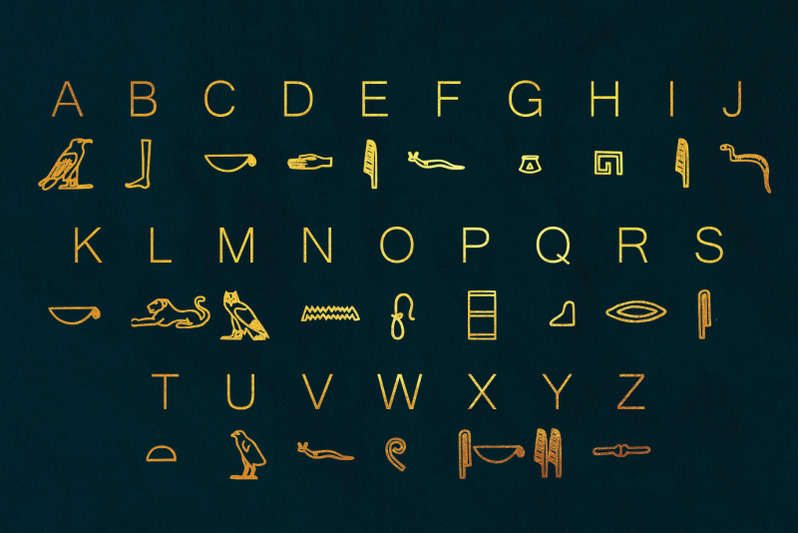
Шрифты для художников оформителей
Введение
История шрифта неразрывно связана с историей письменности, возникновение которой относится к глубокой древности. Письмо как система письменных знаков, передающих речь человека и рассчитанных на зрительное восприятие, возникло из потребности закреплять в памяти какие-либо события, передавать важные известия, указывать дорогу, предупреждать об опасности и т. д.
Первыми письменными знаками, которыми наши далекие предки пользовались для передачи различных сообщений, были рисунки — пиктография, образно-картинное письмо, в котором определенные события изображались в виде примитивного и условного рисунка. Пиктография до самого последнего времени употреблялась у североамериканских индейцев.
Пиктографии
В процессе дальнейшего развития пиктография постепенно вытесняется системой знаков, более точных и дающих более широкие возможности для обозначения предметов и понятий — идеографией, знаками которой служили отдельные реалистические изображения, обозначавшие сначала только названия предметов, а затем и названия действий.
Древнейшей системой идеографического письма является письменность народов Древнего Египта. Знаками этой письменности были иероглифы, которые рисовали и вырезали с большим искусством. Они представляли собой изображения предметов, растений, животных.
Египетские иероглифы
Стремление к упрощению начертания знаков и к ускорению процесса писания привело к тому, что иероглиф в египетском письме стал употребляться для обозначения не слова и даже не слога, а только одного звука. Поэтому принято считать египетское иероглифическое письмо родоначальником буквенных алфавитов.
Упрощенное начертание иероглифических знаков получило название иератического (или жреческого) письма. Это письмо использовалось только для светских книг и в личной переписке, а религиозные книги по-прежнему писали иероглифами. Из иератического письма в дальнейшем выработалась скоропись, или так называемое демотическое письмо.
Иератическое письмо
Древние египтяне впервые стали употреблять для письма папирус — материал, изготовленный из тростникового растения.
На длинных листках и полосах папируса писали палочками черными чернилами или цветными красками. Исписанные с одной стороны листы папируса навертывали на тонкие круглые палки и хранили в особых футлярах из кожи или дерева.
В начале XX в. были открыты так называемые синайские надписи, относящиеся к XIV–XIII вв. до н. э. Знаки этих надписей во многом напоминают египетские иероглифы, но их система представляет собой законченный алфавит, т. е. группу знаков, принятых для обозначения звуков речи и расположенных в определенном порядке. Создателями этого наиболее древнего алфавита были гиксосы — полукочевой прасемитический народ. Они завоевали Египет и господствовали там несколько столетий, пока не были изгнаны египтянами. Гиксосы восприняли высокую египетскую культуру и на основе египетских иероглифов создали свою письменность, основой которой явился алфавит.
Финикийцы, ведшие широкую торговлю со многими странами, значительно улучшили древнесемитическую письменность, сделав ее исключительно фонетической.
В фонетическом письме каждый отдельный графический знак соответствует звуку речи. Это такой вид письма, каким пользуются в большинстве стран мира в настоящее время.
Финикийское письмо
Наш современный алфавит является результатом сложного и длительного развития письменности. Начертание каждой буквы алфавита не является произвольным, а получилось путем упрощения определенного иероглифа, прообразом которого явилась форма какого-либо конкретного предмета.
Например, упрощенная фигура льва (по-египетски «лабу») стала обозначать букву-звук Л; фигура орла (по-египетски «ахом») — букву-звук А и т. д. Знак А послужил прототипом буквы «альфа» в греческом алфавите, «аз» — в древнеславянском.
Упрощение знака «сова» в египетском письме
В этом кроется необычайная стойкость рисунка букв. Мы можем изменить пропорции и контрастность, можем модернизировать и стилизовать буквы, усложнить или упростить их, но мы не можем заменить их составные части другими, выдуманными нами.
Рисунки букв находятся в прямой зависимости от того, на каком материале и какими инструментами эти буквы написаны, какой художник писал их, в какое историческое время. Шрифт, высеченный на камне, отличается от такого же шрифта, написанного кистью на бумаге, шрифты рукописных книг отличаются от печатных шрифтов.
Шрифт, как и архитектура, является зеркалом своего времени.
Исторические изменения также находят в нем свое выражение. Однако изменения, которым подвергается шрифт в своем развитии, касаются не существа буквы, а ее чисто внешних особенностей. Интересно в этой связи проследить, как развивалось и совершенствовалось наше письмо, как на протяжении многих веков из египетских иероглифов вырабатывался шрифт, как современные буквы приобрели привычные нам устойчивые формы.
В первобытные времена рисовали и вырезали письмена на деревьях, скалах и жилищах. Древнеегипетские иероглифы сохранились на стенах храмов и на гробницах. Их наносили на камень в виде рельефа, иногда исполняли красками.![]()